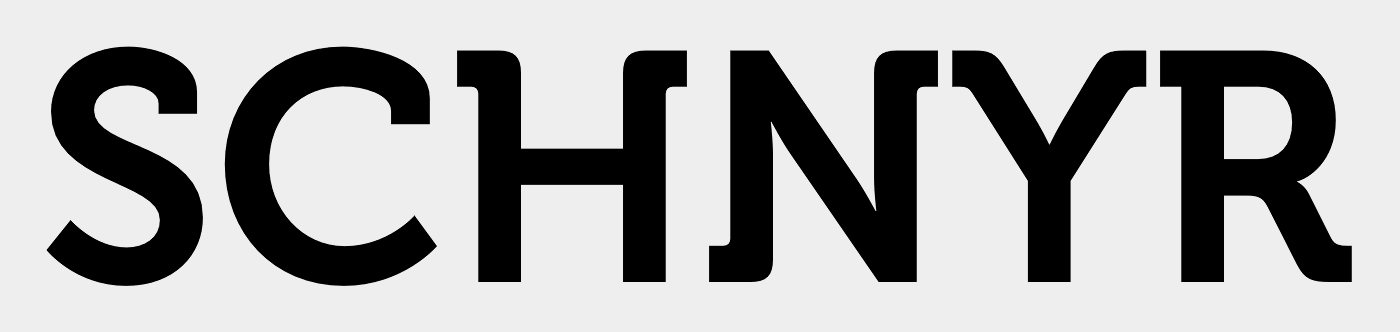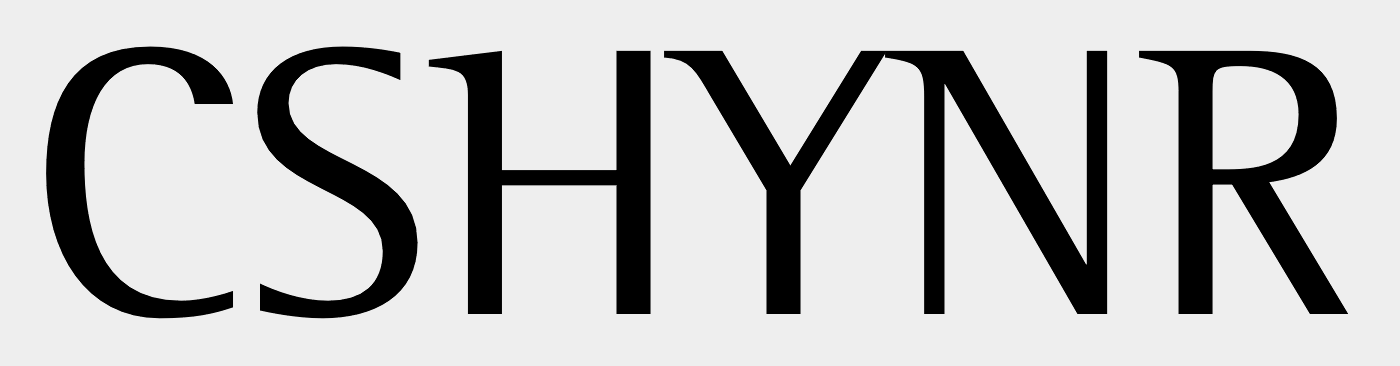
Serifenlose Schrift mit halben Serifen bei einigen Buchstaben
ich suche eine Schrift, die von einer Firma verwendet wurde die aber bereits bankrott ist und ich finde kein Beispiel mehr von deren Logo im Netz...
Die Schrift war recht markant weil Sie an den Buchstaben Y, N und R (könnte sein, dass ich einen oder zwei vergessen habe) jeweils eine halbe Serife (nur auf der linken Seite) hatte. Die anderen Buchstaben sind allerdings serifenlos. Im allgemeinen wirkte die Schrift eher technisch und ging in Richtung Normschrift.
An was ich mich sonst noch erinnere:
1. das C war vertikal abgeschnitten endend
2. keine Dickengleiche Schrift
3. das S war nicht hinunter gekrümmt und lief gerade aus (hoffe Ihr versteht was ich meine)
4. der Querstrich vom H war leicht unterhalb der Mitte und minimal nach oben gebogen
Ich bezweifle leider sehr, dass wir auf dieser mageren Basis etwas finden werden! Gibt es nicht vielleicht irgendwelche weiteren Hinweise? Ich vermute zwar, dass Du den Namen nicht mehr weißt, sonst hättest Du natürlich alle benötigten Buchstaben parat. Aber kannst Du Dich vielleicht erinnern, in welchem Bereich diese Firma tätig war? Spielzeug, Kleidung, Unterhaltung etc.? Kannst Du Dich an Farben erinnern? Wo hast Du dieses Logo gesehen – an Fassaden, in Anzeigen, online? Ist es ein deutsches Unternehmen gewesen oder ein internationales? Jede zusätzliche Information erhöht die Chance, das irgendeinem von uns ein Geistesblitz  kommt.
Man muss dazu, aber das wird Dir bewusst sein, auch noch sagen, dass Logoschriften sehr oft individuell für das Logo gestaltet wurden und keiner bekannten Satzschrift entspringen. :-)
Nachdem das ein kleiner Dienstleister in Polen war denke ich finden wir alle nichts mehr. Fragt einfach nach bestimmten Merkmalen - eventuell fällt mir dann noch mehr ein...
Bei Y und R ging unten eine Serife nach links weg. Beim N auch, allerdings nur unten nach links und oben bei der rechten vertikalen Linie war keine Serife.
Die Schrift wurde auch für die Korrespondenz verwendet soweit ich mich noch korrekt erinnere.
Nachdem das ein kleiner Dienstleister in Polen war denke ich finden wir alle nichts mehr.
Bei meinen oben aufgeführten Fragen ging es mir nicht primär darum, dass wir mithilfe der Antworten im Netz noch Bildmaterial finden könnten, sondern darum, dass diese Hinweise einen von uns darauf bringen könnten, wo er den Schriftzug schon einmal gesehen hat. Auf diese Weise könnten weitere Erkenntnisse/Erinnerungen der Kollegen zur gesuchten Schrift auftauchen.
Im allgemeinen wirkte die Schrift eher technisch und ging in Richtung Normschrift.
Mein spontaner Einfall beim Stichwort »Semi-Sans«:
TheMix von LucasFonts
Und jenes Exemplar hatte ich heute erst zwischen den Fingern:
Rockeby Semi-Serif
Passt allerdings auch nicht 100 % zur Beschreibung. Was den ohnehin schon hohen Schwierigkeitsgrad ohne Abbildung noch weiter in die Höhe treibt, ist ja der letzte Stichpunkt:
der Querstrich vom H war leicht unterhalb der Mitte und minimal nach oben gebogen
S, das oben und unten quasi horizontal ausläuft
H mit dem tieferen Querstrich leicht gebogen
N mit der ganz untypischen Serife und die Punkte an denen sich 2 Linien treffen sind abgeschnitten also weder rund noch spitz sondern gerade abgeschnitten in der horizontalen
R sollte im Bogen runder sein, auch hier die "rückwärts laufende" Serife auf nur einer Seite
Y mit der auffälligen Serife
Und noch eines ist mir eingefallen: Strichstärken sind überall gleich gewesen.
Die ganze Schrift ist gerade und eher technisch, als ob die auf einen Plan gehört.